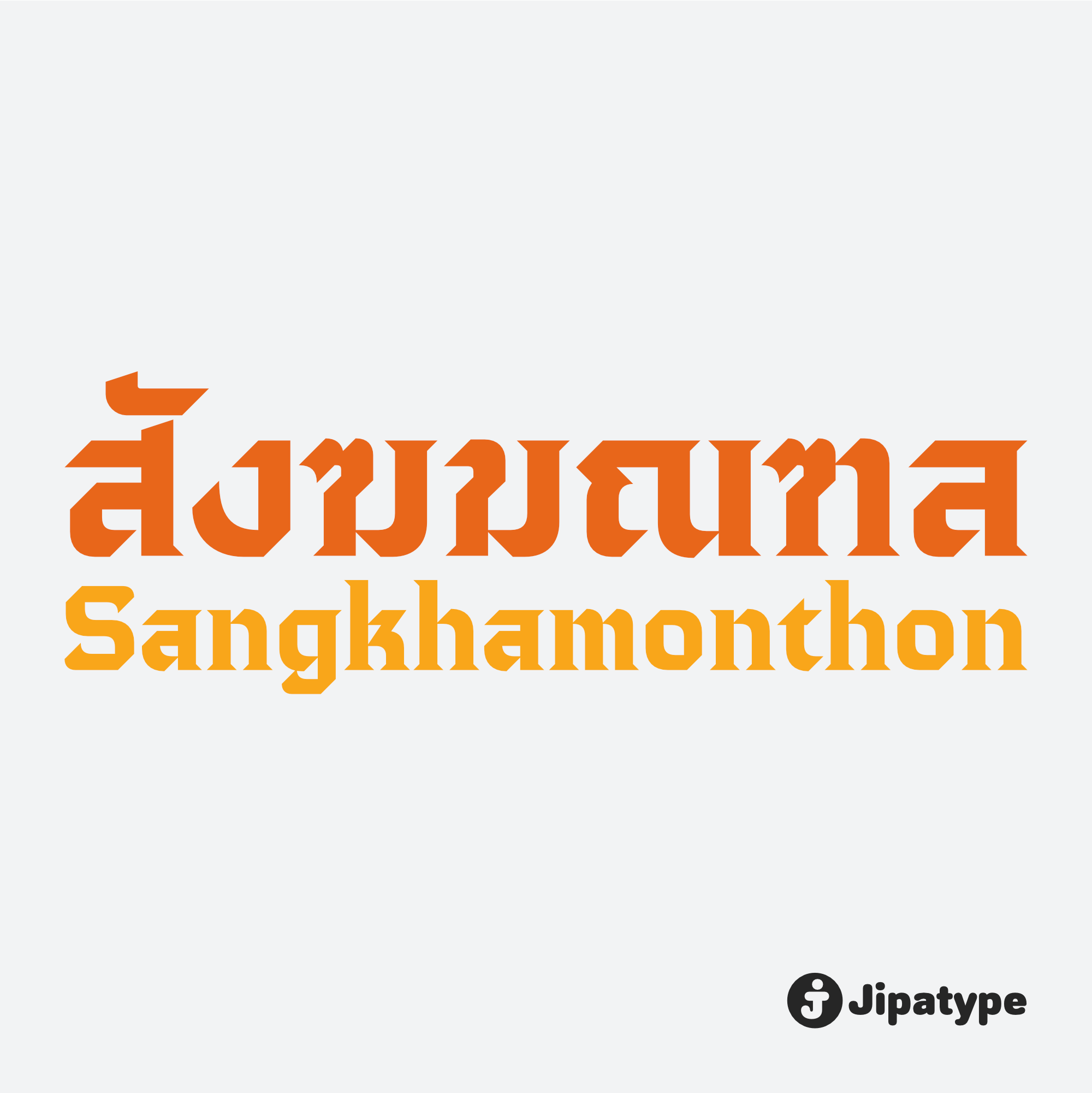
สังฆมณฑล | Sangkhamonthon
ชื่อฟอนต์ : สังฆมณฑล | Sangkhamonthon
สังฆมณฑล เป็นอักษรแบบพาดหัวมีรูปลักษณ์ที่ให้ความรู้สึกขลัง ศักดิ์สิทธิ์ ปลายตัดคม ที่ 45 องศา เลียนแบบการเขียนด้วยปากหัวตัด ผสมผสานกับรูปลักษณ์แบบมาตรฐาน เหมาะสำหรับการนำไปใช้พาดหัวบนสื่อต่าง ๆ ที่เน้นไปทางความเชื่อ ความศรัทธา